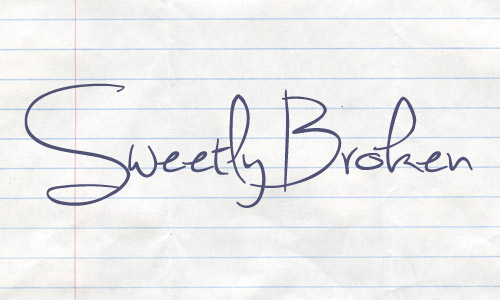
レタリングにこだわるWebデザイナー必見!手書き風フリーフォント25選【無料で使える】
Line25のWebデザインチュートリアル内での注釈付きコード例でどのようなフォントを使っているのかいつも尋ねられるので、手描き風フォント集をつくれば非常に便利だと考えました。この投稿では、さまざまな手書きスタイルをベースにした、さまざまなフリーの手書きフォントを紹介します。ノートやパーソナルメッセージの形でデザインに人間らしさを加えるフォントが必要な時には、このフォント集の中からぴったりのフォントが見つけてください。
@ font-faceルールとさまざまなWebフォントサービスのおかげで、HelveticaとGeorgia以外のフォントを選択できるようになり、Webデザイン用のカスタムWebフォントが爆発的に増加してきています。最近ではWebタイポグラフィについては無数の選択肢があり、手書きフォントの人気はますます高まってきています。
Webタイポグラフィの世界は飛躍的に進歩してきています。既に私たちにはSiFR、Cufon、Typekit、@ font-faceといった選択肢があり、GoogleでさえGoogle Font APIの下で独自のカスタムフォントサービスを導入しています。これらの無料の手書きフォントが、皆さんのウェブサイトのデザインにもっと人間的な雰囲気を与えられることを願っています。
Jenna Sue
これは、フォント字体のデザインのおかげで、皆さんのプロジェクトを優雅に見せることのできる素晴らしいフォントです。手放すことのできない、本当に素敵な手書き風フォントです。
Hand of Sean
Hand of Seanの手は手書き風太字フォントであり、間違いなく様々なクリエイティブな方法で使用できます。これは、フォントコレクションの重要な資産となります。ダウンロードして、皆さんのデザインプロジェクトがどれほどすぐに進化するのか試してみてください
Daniel
Danielは皆さんのプロジェクトをすばらしく見せてくれる手書き風細字フォントです。現在進行中プロジェクトでこのフォントを使用することができるか細かく分析してみましょう。あるいは後のためにとりあえずダウンロードとインストールをしてもよいでしょう。
GoodDog
これはあなたのフォントバリエーションの重要な資産になる可能性のあるもう一つのすばらしい手書き風太字フォントです。このフォントを使うことによって、デザインプロジェクトが改良できる方法がどれだけ沢山あるのかは未知数です。
Sweetly Broken
これは間違いなく皆さんのデザインプロジェクトにエレガントな感じを与えることができるかわいいフォントです。Sweetly Brokenは、皆さんが今までずっと探しつづけてきたものかもしれません。
Lovely Eunike Hans
これは皆さんのフォントコレクションに是非加えておきたいもう一つのクールな手書き風太字フォントです。
Max’s  Handwrittin
Max’s Handwrittinは皆さんがまさにずっと探し続けてきたものかもしれない、クールな手書きフォントです。レタリングは素晴らしく、このフォントのクリエイティブな使い方は無限にあります。
Angelina
フォントのデザインによって、皆さんのプロジェクトを優雅に見せることのできる素晴らしいフォントです。 皆さんのコレクションに加えておくべき、本当に素敵な手書き風フォントです。
Journal
この手書き風フォントが、プロジェクトを興味深くてパーソナライズされたものにしてくれるのは間違いありません。 手作り感が必要なプロジェクトに最適な、パーソナルな感じで、無駄のないスクリプトフォントです。
Jinky
Jinkyは、クリエイティブな様々な方法で使用できる本当に素敵なフォントであり、フォントコレクションの大切な資産となります。 ダウンロードして、皆さんのデザインプロジェクトを一瞬の内に進化させましょう。
Throw My Hands Up in the Air
これは皆さんのフォントコレクションに加えておくべきクールな名前の素晴らしいフォントです。 このフォントは、デザインプロジェクトに手書きのフォントを追加したい場合に最適です。
Christopher Hand
このフォントは、皆さんのデザインプロジェクトに欠けていたものかもしれません! Christopher Handをチェックして、これがあなたのプロジェクトに相応しいフォントであるかどうかを確認してください!
Joy Like Sunshine Through My Windowpane
このフォントには、レタリングがどのようにデザインされたのかを最もよく表している長い名前がつけられています。窓ガラスに差し込む日差しのような喜びに満ちた気持ちに満ちています。
The Great Escape
The Great Excapeは皆さんのコレクションに加えておく価値のある本当に素敵な手書きフォントです。
Akbar
このフォントは、皆さんのフォントコレクションにとって貴重な資産になります。このフォントをダウンロードして、皆さんのデザインプロジェクトを一瞬のうちに進歩させましょう。
Talking to the Moon
このフォントは非常にエレガントなレタリングが施されています。大変便利で、皆さんのプロジェクトを本当に美しく見せることができます。
Dear Joe
Dear Joeは、間違いなく皆さんのプロジェクトをより良く見せることができるエレガントな手書き風フォントです。この素敵なスクリプトフォントはシンプルにデザインされていて、このフォントを特別なものにしている独特の細部を持っています。
Gunny Rewritten
これはGunnyフォントの新しいバージョンであり、コレクションに加える価値のあるフォントです。フォントをダウンロードして試してみて、このフォントがプロジェクトでどれほど多様な方法でクリエイティブに活用できるか試してみましょう。
Skinny
Skinnyは、非常に多くの創造的な方法で使用することができる本当に素敵な細字フォントです。皆さんのフリーフォントコレクションに是非加えておくべきフォントです。
A Year Without Rain
これは皆さんのコレクションに常に加えておくべきエレガントな手書きフォントです。 このフォントは様々な創造的な方法で使用することができ、間違いなくあらゆるプロジェクトを改良することができます。
Yank
他にクールな手書き風フォントを探していたなら、これがぴったりかもしれません。
Faraco Hand
最後になりましたが、Faraco Handはあなたのコレクションに入れるべき素敵な手書き風フォントです。
Declara
これはあなたのコレクションから手放すことのできない本当に素晴らしいフォントです。 レタリングはとてもエレガントで、デザインプロジェクトを確実に改善することができます。